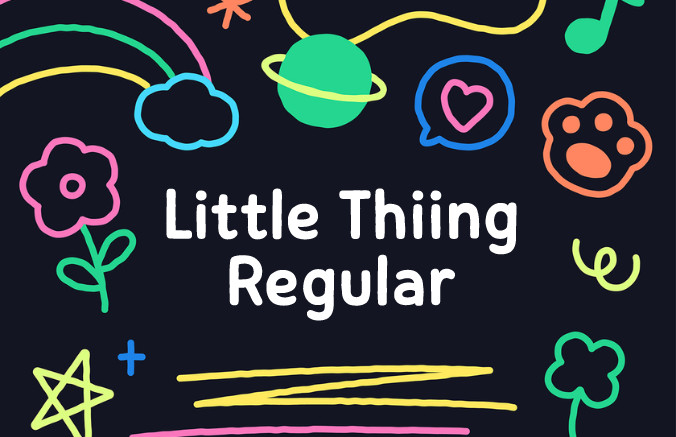
Font Tiếng Việt Little-thiing Regular
Khám phá sức hút của Font Tiếng Việt Little-thiing Regular trong thiết kế học đường
Tổng quan về bộ Font Tiếng Việt Little-thiing Regular
Trong thế giới đồ họa hiện đại, việc tìm kiếm một mẫu Font Miễn Phí có phong cách nhẹ nhàng và gần gũi luôn là ưu tiên hàng đầu của các bạn học sinh. Font Tiếng Việt Little-thiing Regular nổi lên như một lựa chọn hoàn hảo nhờ những đường nét thanh mảnh, uốn lượn tự nhiên giống như chữ viết tay. Bộ font này mang đến cảm giác thân thiện, giúp các bài thuyết trình hay báo tường trở nên sinh động và có hồn hơn bao giờ hết.
Đặc điểm nổi bật của phông chữ
Điểm mạnh nhất của Font Tiếng Việt Little-thiing Regular chính là khả năng hiển thị tiếng Việt trọn vẹn, không bị lỗi dấu – một vấn đề thường gặp ở các font ngoại nhập. Với định dạng Regular tiêu chuẩn, các ký tự có độ dày vừa phải, tạo sự cân đối cho văn bản. Đây là công cụ đắc lực để trang trí các ghi chú học tập hoặc thiết kế thiệp chúc mừng thầy cô, bạn bè vào những dịp lễ đặc biệt.
Cách ứng dụng Font Tiếng Việt Little-thiing Regular hiệu quả
Lưu ý khi sử dụng trong trình bày
Dù có tính thẩm mỹ cao, bạn chỉ nên dùng font cho các đoạn văn ngắn hoặc tiêu đề trang trí. Tránh sử dụng cho các văn bản dài để đảm bảo người đọc không bị mỏi mắt, giữ cho bố cục luôn thoáng đãng.
Kết luận về bộ phông chữ hữu ích